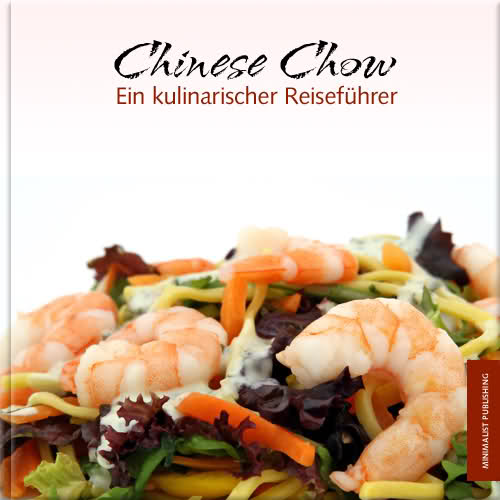
Kulinarischer Reiseführer
Ich studiere Werbung & Marketing im 1.Semester. Im Fach Typografie haben wir eine kleine Hausarbeit aufgekriegt. Wir sollen einen kulinarischen Reiseführer erstellen. Ich hab das Land China gewählt, so nebenbei. Meine Frage, da es ja perfekt sein muss , welche Schriftart eignet sich dafür am Besten? Sowohl für das Deckblatt als auch für die 2 Innenseiten.
Naja... Klischeehaft wäre eine Pinselschrift auf dem Deckblatt, für den Innenteil würde ich in jedem Fall drauf verzichten etwas "zu asiatisches" zu verwenden... Nimm etwas gut lesbares mit "Flow" :)
Hier ein Beispiel dafür, dass man nicht NUR mit Klischees arbeiten muss: http://www.thong-thai.com/ :D
Vielleicht findest Du hier http://www.dafont.com/theme.php?cat=604 was brauchbares für den Titel, und schau Dir mal die hier http://www.dmjx.dk/presserum/skrift.html und diese http://mplus-fonts.sourceforge.jp/mplus-outline-fonts/download/index.html für den Fließtext an...
Und generell findest Du bei smashing magazine Artikel über Freefonts, dürfte am besten sein Du stöberst selbst einmal und lässt Dich inspirieren :)
Vielleicht magst Du auch zur Inspiration mal nach "graphic design china" googeln, um zu sehen was im Land so gemacht wird... habe so z.B. diese zwei Sachen gefunden: http://www.designbrandchina.com/ und http://pingmag.jp/2008/04/14/new-graphic-design-in-china/ .
die richtige(?) Katogorie bei Dafont ist ,,Foreign Look''.
Da gibt es dann paar ,,dekokackige'' Pinselschriften:
und viele mehr ... Aber ist das wirklich so toll?
Und da gibt es ein paar nette Grotesken:
Bzgl des bereits genannten Beispiels ist mir die Optima als Reisschrift eingefallen. Sinnvoll? Ich finde die Frage sehr interessant ... und hoffe hier auch ein paar Anworten zu finden.
@Uwe:
Genau diese Kategorie wollte ich vermeiden ;) Es ist ja nicht sooo schlimm, mit Klischees zu arbeiten, aber ich denke, mit dem selben Schreibwerkzeug zu arbeiten (sozusagen) muss reichen, es muss nicht auch noch nach kaputtgegangenen chinesischen Zeichen aussehen ;)
Optima ist schön... :) Aber damit verbinde ich eigentlich eine ganz andere Optik als dass ich sie als Reisschrift verwenden würde... Ich habe das Gefühl, dass eine Serifenlose in gleichbleibender Strichstärke besser passen würde, als Kontrast zum Pinsel sozusagen :)
Es ist aber auch echt nicht notwendig überhaupt eine Pinselschrift zu verwenden :D
welche Schriftart eignet sich dafür am Besten?
leider gibt es nicht DIE schrift für kulinarische reiseführer, es kommt ja auch immer auf die gestaltung an bzw. was du für eigene ideen einfließen lässt.
Meine Angabe kann zielgerichtet ins Klischee führen. Daher auch das Fragezeichen ob ich Dich richtig verstanden haben. Aber die Kategorie kann auch eine sinnvolle Dekoschrift zu Tage bringen. Ich würde die Osaka Sans durchaus mal genauer ins Auge fassen. Als Dekorative Schrift in einem Balken an der Seite von Oben nach Unten könnte die durchaus was hermachen. Vorsicht ist aber trotzdem angesagt. Das ungeübte Spielen mit dekorativen Schriften, Cliparts und Messern kann übel ins Auge gehen.
Aber zurück zur Reisschrift: Humanistische Grotesk? Wie würde eine Syntax funktionieren? Oder eine Gill Sans (condensed)? Gill Sans Infant Font? Oder die Fiendstar? http://www.linotype.com/de/510084/fiendstar-schriftfamilie.html Habe ich Dich da wenigsten richtig verstanden?
Heh... :D Auf den ersten Blick war meine Assoziation eher Bladerunner... :D
Syntax ist schön... Wie wär's so?
in dem gezeigten Buchcover nimmt das Bild sehr viel Platz ein und die Schrift wirkt stark an den Rand gedrängt. Da wäre IMHO noch Verbesserungspotenzial. Ansonsten verzichtet es aber auf unnötige Dekokacke und ist schön übersichtlich ... bis auf das Problem der an den Rand gedrängten Schrift.
Gedankenspiel: Stelle Dir den Titel am rechten Rand des Buches wie eine Leuchtreklame von Oben nach Unten vor. Der Rest würde dann so bleiben wie auf dem von Dir vorgestellten Cover.
Jaha... das hab ich auch gesehen, nachdem ich das Bild schon hochgeladen hatte... da hat dann die Faulheit gesiegt ;)
Insgesamt war das lediglich eine 5-Minuten-Arbeit, das Bild ist der Google Bildersuche entsprungen... was besseres hab ich auf die Schnelle nicht gefunden ;)
@Bertel: Das ist aber echt lieb und großzügig von Dir :D Da hab ich mich doch glatt hinreißen lassen, auf sxc.hu ein Bild raus zu suchen und noch mal kurz zu basteln. Ist zwar relativ grässlich (naja, vorher wars auch nicht besser...), aber es soll ja auch nur meinen Gedankengang verdeutlichen :)